싸인은 단순한 이름을 적는 것이 아니라, 우리의 성격과 개성을 반영하는 중요한 요소예요. 🖊 어떤 사람은 크고 화려한 싸인을 선호하고, 어떤 사람은 작고 단순한 싸인을 사용하죠. 이 차이는 단순한 습관이 아니라, 성격과 심리 상태를 보여주는 신호일 수 있어요. 그래서 싸인을 보면 그 사람의 성격을 추측할 수 있다는 말도 있답니다!
싸인의 크기, 필체, 기울기, 꾸밈 정도에 따라 사람의 성향을 알 수 있다고 해요. 예를 들어, 크고 강한 필체의 싸인은 자신감 넘치는 성격을 나타내고, 작고 조용한 싸인은 섬세하고 내성적인 성격을 반영할 가능성이 높아요. 그럼 싸인과 성격의 관계를 깊이 있게 알아볼까요? 🔍
싸인과 성격의 관계 🔎
우리가 무의식적으로 하는 행동에는 성격이 반영되는데, 싸인도 그중 하나예요. 사람마다 글씨체가 다르듯이, 싸인도 각자의 개성과 심리가 반영되어 있죠. 싸인을 분석하면 성격을 파악하는 데 도움이 될 수도 있어요. 🤔
예를 들어, 크게 쓰는 사람과 작게 쓰는 사람의 성격이 다르듯, 싸인의 크기와 형태도 그 사람의 성향을 보여준다고 해요. 또한, 싸인의 기울기, 곡선 여부, 선의 강약도 중요한 요소로 작용해요.
📌 싸인의 요소별 성격 분석 🧐
싸인 요소 특징 연관된 성격 크기 (큰 싸인) 공간을 넓게 차지함 자신감, 외향적 크기 (작은 싸인) 작고 단정한 형태 신중함, 내성적 기울기 (오른쪽으로 기울음) 긍정적, 개방적 외향적, 적극적 기울기 (왼쪽으로 기울음) 내성적, 신중함 보수적, 조심스러움 곡선 많은 싸인 부드러운 필기체 감성적, 유연한 성격 직선적인 싸인 각진 형태, 강한 선 결단력, 논리적 이처럼 싸인의 형태와 스타일에 따라 성격이 드러나죠. 그렇다면 싸인 스타일별로 더 구체적으로 성격을 분석해 볼까요? 🤩
싸인 스타일별 성격 분석 🖊
싸인의 스타일은 사람의 성향을 보여주는 중요한 요소예요. 어떤 사람은 단순한 선 몇 개로 싸인을 만들고, 어떤 사람은 복잡하고 화려한 디자인을 선호하죠. 싸인의 스타일에 따라 어떤 성격이 반영되는지 살펴볼까요? 👀
🔎 싸인 스타일과 성격 유형 🏷
싸인 스타일 특징 연관된 성격 단순하고 직선적인 싸인 불필요한 장식 없이 짧고 직선적 직설적, 현실적, 논리적 곡선이 많은 싸인 부드러운 필체, 둥근 곡선 활용 감성적, 친근함, 유연한 사고 화려하고 복잡한 싸인 장식적인 요소가 많고 독창적 창의적, 예술적, 개성 강함 짧고 간결한 싸인 한두 글자로 빠르게 적음 효율적, 실용적, 활동적 긴 싸인 전체 이름을 길게 쓰거나 세밀하게 디자인 신중함, 꼼꼼함, 디테일 중시 기울어진 싸인 오른쪽 또는 왼쪽으로 기울어짐 적극적(오른쪽), 조심스러움(왼쪽) 싸인의 스타일을 보면 사람의 성격이 보이는 것 같지 않나요? 그렇다면 필적학(그래포로지, Graphology)에서는 싸인을 어떻게 해석할까요? 🔍
필적학이 말하는 싸인의 의미 🔬
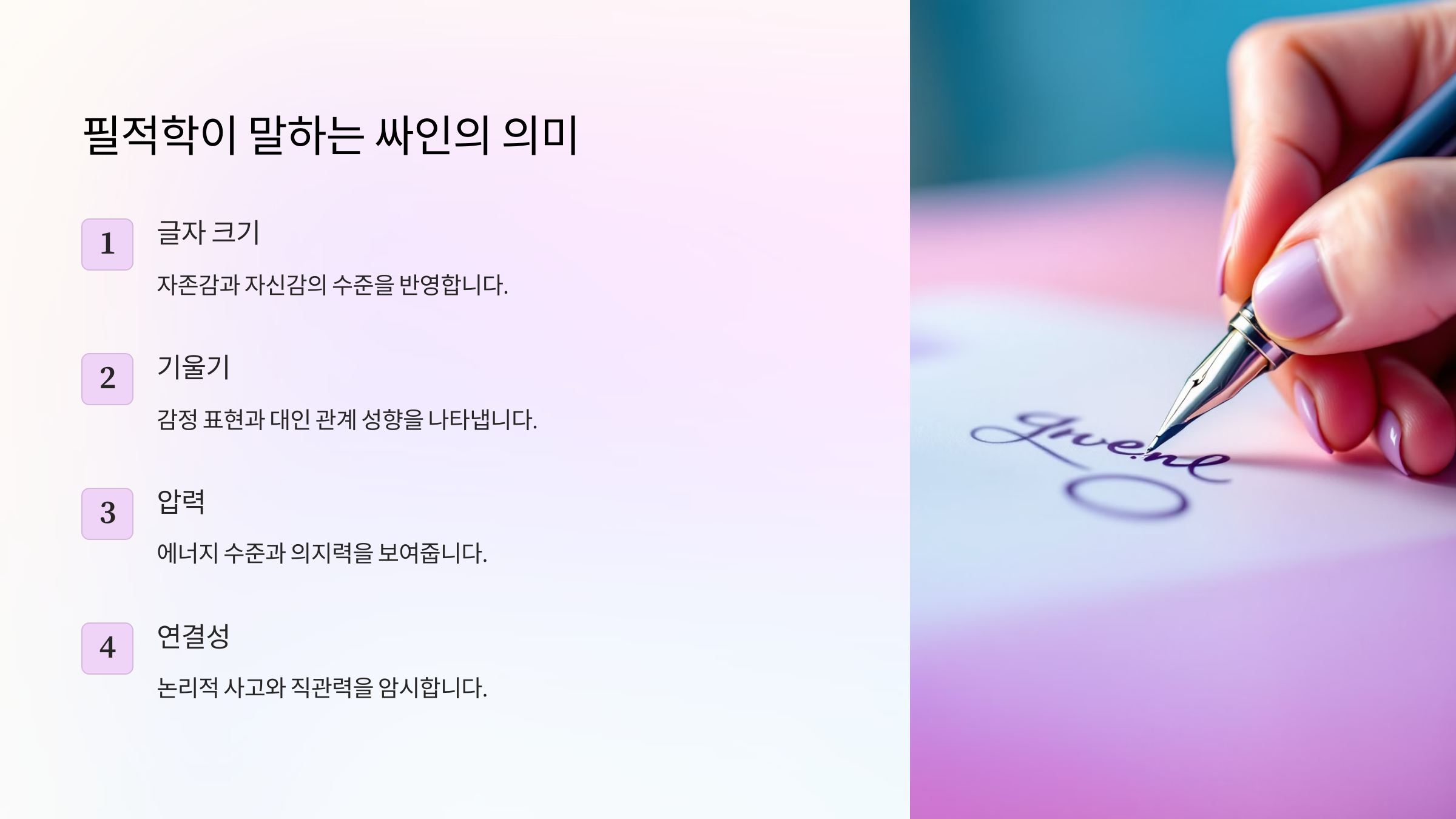
필적학(Graphology)은 글씨체를 분석해 성격과 심리를 연구하는 학문이에요. 싸인의 모양과 필체를 통해 그 사람의 심리 상태를 읽어낼 수 있다고 해요. 심리학과 연결되어 있어 법률, 범죄 수사에도 사용된답니다. 🕵♂
필적학에서는 싸인의 크기, 기울기, 강약, 곡선 여부 등을 통해 그 사람이 내성적인지, 외향적인지, 창의적인지 등을 분석할 수 있다고 해요.
🧠 필적학적 싸인 분석 사례 🔍
싸인 특징 해석 싸인의 첫 글자가 크고 강조됨 자신감 있고 리더십 강한 성격 싸인이 끝으로 갈수록 점점 작아짐 소심하고 신중한 성향 싸인에 밑줄이 강하게 들어감 확신이 강하고 자기 주장이 뚜렷함 싸인에 불필요한 장식이 많음 창의적이고 예술적 감각이 뛰어남 싸인이 둥글고 부드러운 곡선이 많음 사교적이고 감성적인 성격 싸인이 각지고 직선적임 논리적이고 분석적인 성향 이처럼 싸인은 단순한 글씨가 아니라, 우리의 성격과 감정을 담고 있는 중요한 요소예요. 이제 유명인의 싸인을 보면서 성격과 스타일을 어떻게 반영했는지 알아볼까요? 🌟
유명인의 싸인과 성격 분석 🌟
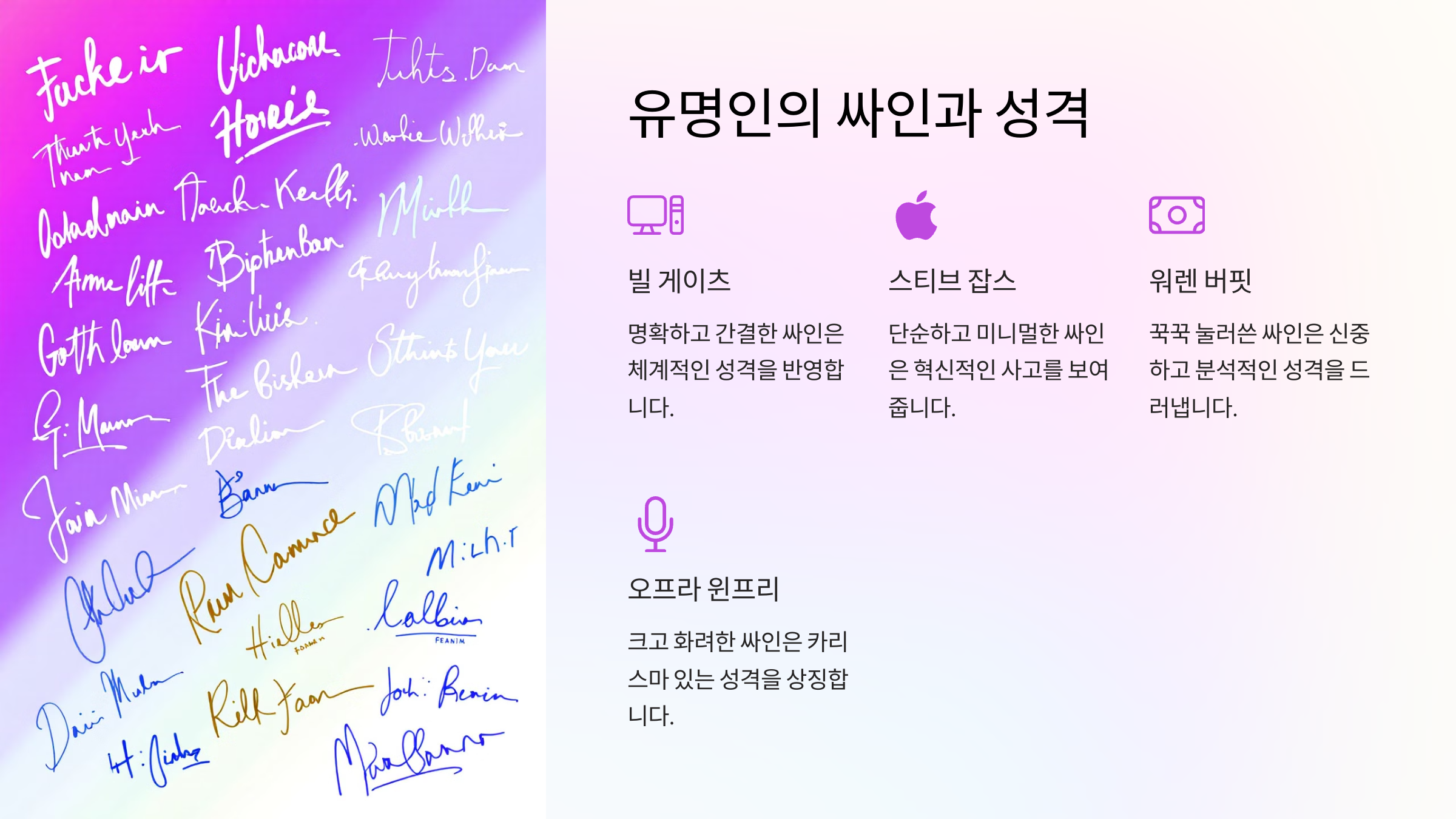
유명인들의 싸인은 단순한 서명이 아니라, 그들의 개성과 브랜드를 나타내는 시그니처(Signature) 디자인이기도 해요. 그럼 세계적으로 유명한 인물들의 싸인을 살펴보면서, 그 싸인 속에 담긴 성격과 특징을 분석해 볼까요? 🔎
🌍 세계적인 유명인의 싸인 분석 ✍
유명인 싸인 스타일 성격적 특징 스티브 잡스 단순하고 깔끔한 필기체 미니멀리즘, 혁신적 사고 도널드 트럼프 각지고 강한 직선 구조 자신감, 강한 리더십 마이클 잭슨 곡선이 많고 장식적인 스타일 창의적, 감성적 엘론 머스크 짧고 단순한 필기체 실용적, 직설적 나폴레옹 크고 웅장한 필체 야망, 지배력 이처럼 싸인은 그 사람의 성격과 가치관을 반영해요. 그렇다면 우리는 어떻게 나만의 개성 있는 싸인을 만들 수 있을까요? 🤩
나만의 개성 있는 싸인 만들기 ✨
싸인을 만들 때 가장 중요한 것은 본인의 개성을 담는 것이에요. 하지만 싸인을 만들다 보면 어떤 스타일이 좋을지 고민될 수 있죠. 🤔 그럴 땐 다음 4가지 요소를 고려해보세요!
🎨 개성 있는 싸인을 위한 4가지 요소 🖋
요소 설명 이니셜 활용 이름의 첫 글자를 강조하면 간결하면서도 강렬한 인상을 줌 기울기 조절 오른쪽 기울기는 적극적인 느낌, 왼쪽 기울기는 신중한 느낌 곡선 vs 직선 곡선이 많으면 부드러운 이미지, 직선이 많으면 강한 인상 특별한 기호 추가 별 ★, 점 . , 밑줄 등으로 개성을 더할 수 있음 자, 이제 여러분도 나만의 개성 있는 싸인을 만들 준비가 되었나요? 😉 마지막으로 싸인의 변화가 성격에 영향을 미칠 수 있는지 알아볼까요?
싸인 스타일이 변하면 성격도 변할까? 🔄
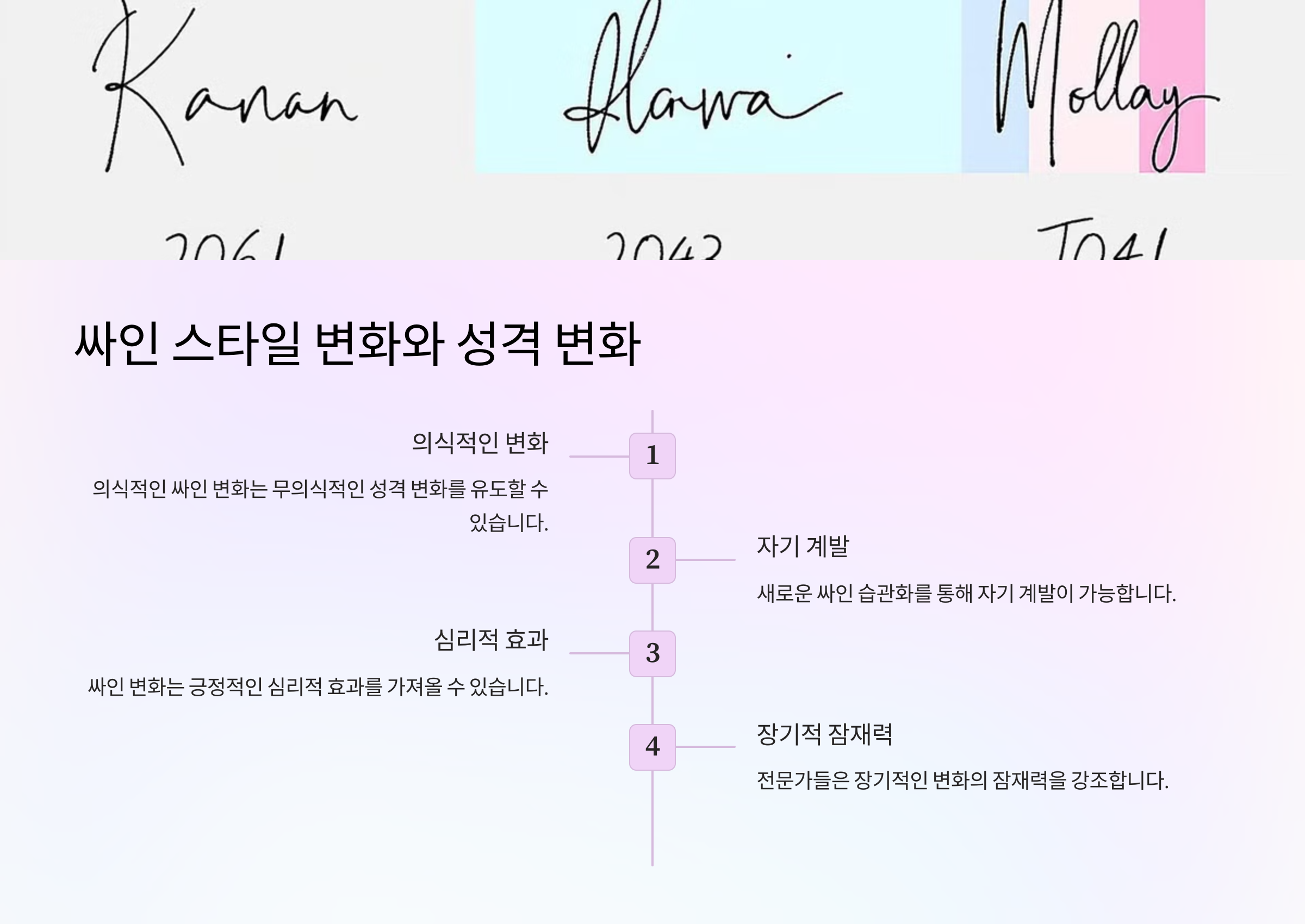
싸인은 오랜 기간 동안 변화할 수 있어요. 사람의 성격이 성숙해지거나 변화하면, 싸인 스타일도 달라질 수 있죠. 그렇다면 싸인을 바꾸면 성격에도 영향을 미칠까요? 🤔
🔄 싸인 스타일 변화와 성격의 관계 📖
변화된 싸인 스타일 성격적 변화 단순한 싸인 → 화려한 싸인 자신감 증가, 창의성 발휘 작은 싸인 → 큰 싸인 자신감 상승, 외향적 성향 곡선 → 직선 논리적 사고 강화, 결단력 향상 기울어진 싸인 → 수평 싸인 안정감 증가, 신중한 성격 FAQ
Q1. 싸인을 바꾸면 운이 좋아진다는 말이 사실인가요?
A1. 직접적인 연관은 없지만, 싸인을 바꾸면서 자신감이 생길 수 있어요!
Q2. 싸인을 너무 복잡하게 하면 불편할까요?
A2. 네, 서류 작성 시 시간이 오래 걸릴 수 있어요.
Q3. 유명인의 싸인을 따라 해도 되나요?
A3. 참고는 가능하지만, 본인만의 스타일을 만드는 것이 좋아요!